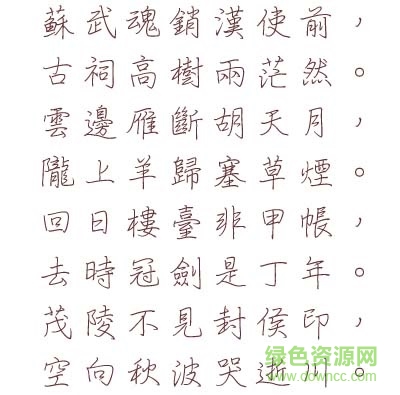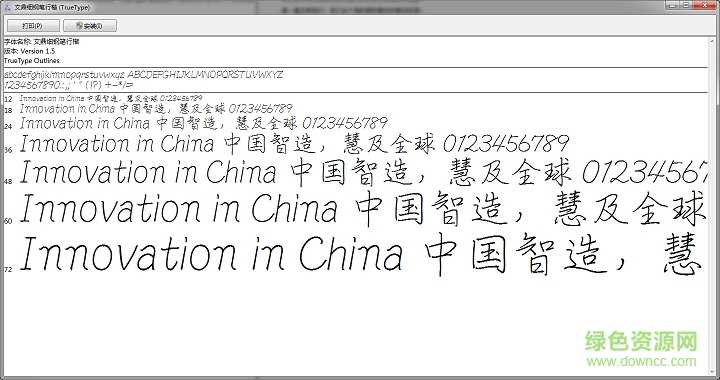
软件介绍 软件标签: 文鼎字体 行楷 字体 文鼎细钢笔行楷字体适用于广告设计、出版印刷、商业用字等多种不同领域,还可以让喜欢钢笔字的用户参照练习,这款字体美观大方,有需要的用户赶快来本站免费下载体验吧!文鼎细钢笔行楷简体字体介绍文鼎细钢笔行楷字体是一款笔画比较细的钢笔字体,给人的感觉非常流畅,适合大家对照练习钢笔字。字体安装说明1、点击打开字体,直接选择安装即可2、将字体复制到C:\Windows\Fonts文件夹即可完成安装。注意事项本站所有字体资源仅供个人学习与参考,如需商业使用请到相关官网授权。 软件截图 上一张下一张(1 / 1) 安装详细截图 猜你喜欢 行楷字体 钢笔字体 行楷字体 行楷字体大全是绿色资源网小编为大家打包整理的行楷字体ttf合集,包含了几十款应用极广的行楷体,适用于影视、广告、平面、印刷各种行业领域,选择多样,下载便捷! 查看更多>> 汉仪苏泽立行楷精修版简 3.01M/中文/4.0/免费版下载 汉仪许静行楷字体 2.44M/中文/4.4/下载 繁体行楷字体大全 46.87M/中文/2.5/下载 经典行楷简体 常规 5.54M/中文/2.3/下载 文星简行楷 3.41M/中文/6.6/下载 stxingkai 3.41M/中文/6.3/免费版下载 钢笔字体 钢笔字体是设计领域经常用到的字体,钢笔字体具有鲜明的个人特征,风格多样,深受广告设计、平面设计师的喜爱,除了一些手写钢笔字体,还有正楷、行书类的钢笔字字体,为设计师们提供了丰富的字体形式,绿色资源网也有很多钢笔字体下载和钢笔字体包,需要的可以看一看 查看更多>> 钢笔书法软件手机版 103.96MB/中文/10.0/v2.2.0 安卓版下载 钢笔之家 4.83M/中文/10.0/v1.0.2 安卓版下载 钢笔手写字体免费 11.71M/中文/1.2/下载 钢笔书法入门基知识 31.79M/中文/5.0/v6.3.1 安卓版下载 浮生体 1.92M/中文/5.0/下载 伯乐钢笔行书字体 3.53M/中文/6.6/下载 其他版本下载 标题 大小 更新日期 下载 下载地址 电脑版 文鼎细钢笔行楷简体 ttf免费版 点击报错 软件无法下载或下载后无法使用,请点击报错,谢谢! 关闭报错反馈 请描述您所遇到的错误,我们将尽快予以修正,谢谢! *必填项,请输入内容 本类最新 文鼎霹雳繁体字体 文鼎妞妞字体 文鼎cs魏碑简 文鼎cs粗圆繁ttf 文鼎cs大黑繁体 文鼎cs舒同体繁字体 相关文章 Photoshop字体安装使用方法和技巧 如何解决“无法新增字体”问题 Win 7系统安装字体方法 网页字体大小设置方法 怎么改网页字体大小 在Linux系统中安装字体的几种方法 windows7字体显示问题:打开某些程序的时候显示的是乱码 用户评论 热门评论 最新评论 发表评论 查看所有评论(0) 昵称: 请不要评论无意义或脏话,我们所有评论会有人工审核. 字数: 0/500 (您的评论需要经过审核才能显示)